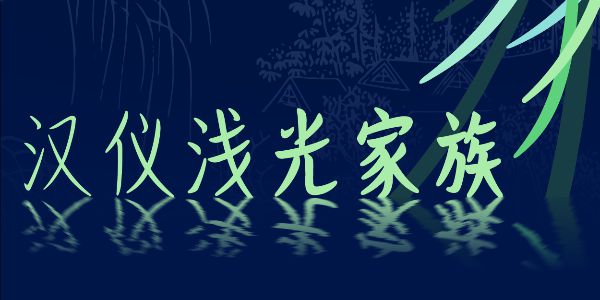
夏夜翩翩的萤火虫,汉仪浅光家族
淡雅 / 闲适 / 灵动 / 清新
标志 / 书籍 / 广告 / 杂志 / 游戏 / 动漫 / 影视 / 包装
汉仪浅光是一款清新优雅、灵动自然的,具有手写风格的字体。曾荣获第二届汉仪字体之星大赛正文组二等奖。该字体笔画自然舒展、简洁轻盈,似早春清风微拂,杨柳兰叶,葳蕤生光。带给人闲和秀润、灵动自然的感觉。造型柔和、富有亲和力,适合用于美妆、服饰、糕点等需要表达温润之美的场合。
汉仪浅光目前已成功实现家族化,从原来的一款细体,衍生到拥有从35到85共六款字重的字体家族。从细体到粗体,更多的字重,可以满足不同视觉层级的需求,为设计师排版提供更丰富的解决方案。
汉仪浅光的字形修长,重心偏高,中宫舒展。让字体透露出了优雅、秀丽和高挑的文艺气质。
字形的整个结构不同于传统的方形结构,而是一种带有弧度的四边形,如同在空中摇曳的风筝般轻盈。所有笔势均向右提收,体现了字形的书写感。字形风格统一,犹如被微风吹拂着的柳叶般充满生机。
汉仪浅光的笔画整体细腻温润。细体起笔收笔淡入淡出,行笔稳定粗细均衡。粗体起笔方润、收笔圆凝。整个家族的字形看起来、灵动飘逸,温润又不呆板,体现出闲和秀润之美。
汉仪浅光的笔画里没有直线,是以细腻生动的弧线组成。笔画结构布置均匀,带给人灵动自然的视觉感受。
作为一款带有手写感的字体,字体中含有大量连笔或点画之间相互呼应的结构。且相同的笔画在不同的字形结构中也有不同的连笔形态。
汉仪浅光新增了多个字重,更加丰富了字体的表现能力。汉仪浅光35细腻如柳叶,优雅灵动、自然舒展。汉仪浅光85则如兰草般温润饱满、绵软柔和。35/45/55的字重适合用在正文,65/75的字适合用在小标题和短文案场合,而85和35版本适合用在标题场合以展示细节。
汉仪浅光的西文部分, 由汉仪字库西文组设计师霍悦昕设计。保留了中文风帆状的结构和淡入淡出的笔画。纵向笔画角度统一,排列在一起非常有节奏感。中西文混排在一起效果十分和谐。